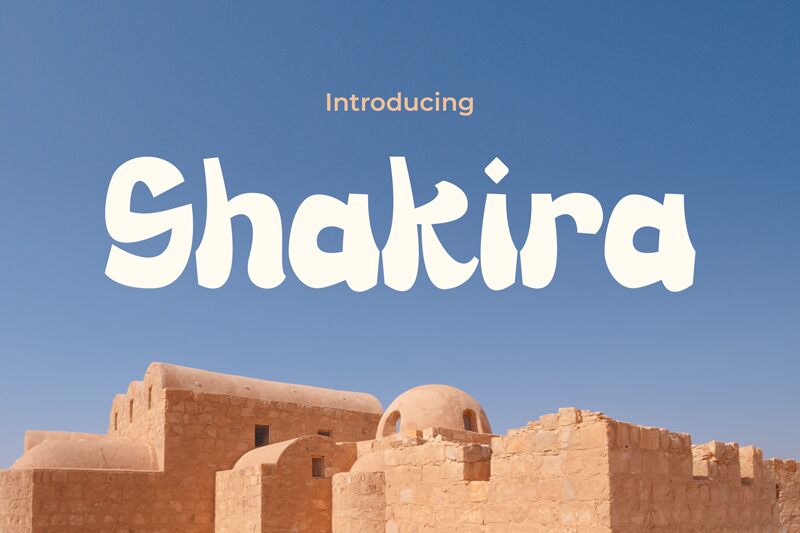
Shakira
Shakira von PINISIART ist eine kostenlose, arabisch inspirierte Display-Schrift mit einem massiven, handgeschnittenen Rhythmus. Die Buchstaben wirken breit und farbsatt, wobei sie abgerundete schwarze Formen mit scharfen, zulaufenden Schnitten und gezielten Akzenten kombinieren. Dies verleiht dem Alphabet eine ausgeprägte kalligrafische Note, ohne den lateinischen Schriftcharakter zu verlieren.
Sie passt perfekt für Musikplakate, Café-Branding, Streetwear-Designs, Albumcover und Event-Flyer, bei denen dieser hybride arabische Look die gesamte Überschrift trägt. Als kostenlose Schrift eignet sich Shakira zudem hervorragend für kurze Titel, Logo-Skizzen und markante Initialen, da ihre schwere Silhouette und die plötzlichen, angewinkelten Schnitte selbst bei wenigen Buchstaben für Dynamik und Fülle sorgen.